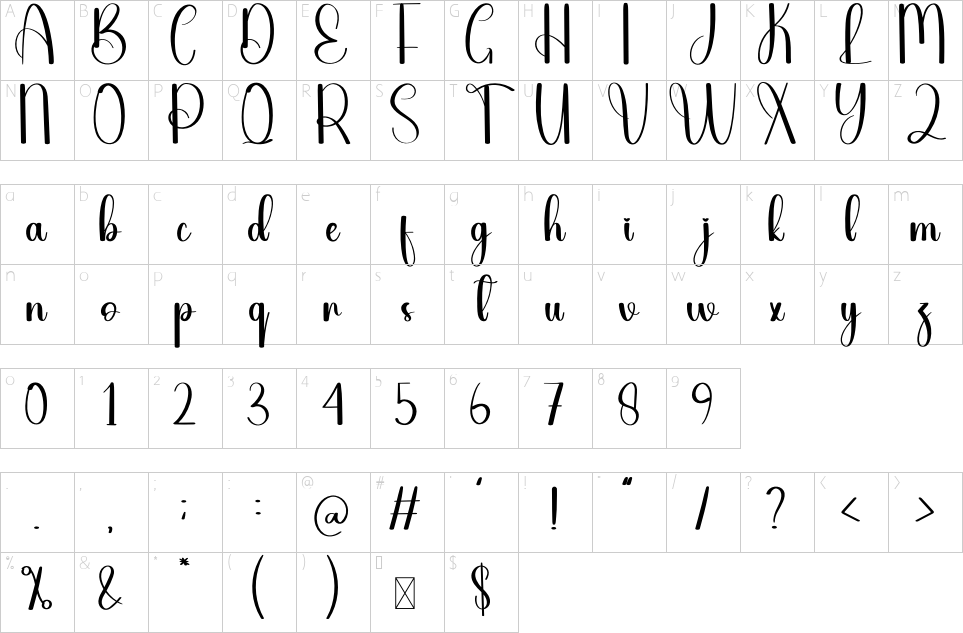
Melamine Font | 1001 Free Fonts – Download Grátis
Aqui está uma descrição em português do Brasil, envolvente e natural, para uma página de download da fonte ‘Melamine Font | 1001 Free Fonts’: A fonte Melamine é um elemento de design que combina uma harmonia clara e alegre com uma leveza moderna. Suas linhas suaves e o seu acabamento suave tornam-se perfeitas para estilos de design gráfico modernos e contemporâneos. Melanine foi criada por um designer desconhecido e pode ser usada gratuitamente tanto no Windows quanto no Mac. Com uma variedade de opções e estilos, a fonte Melanine se encaixa perfeitamente em designs de aplicativos, editoriais e até mesmo em elementos de marca. Download esta fonte agora para adicionar um toque único a seus projetos.